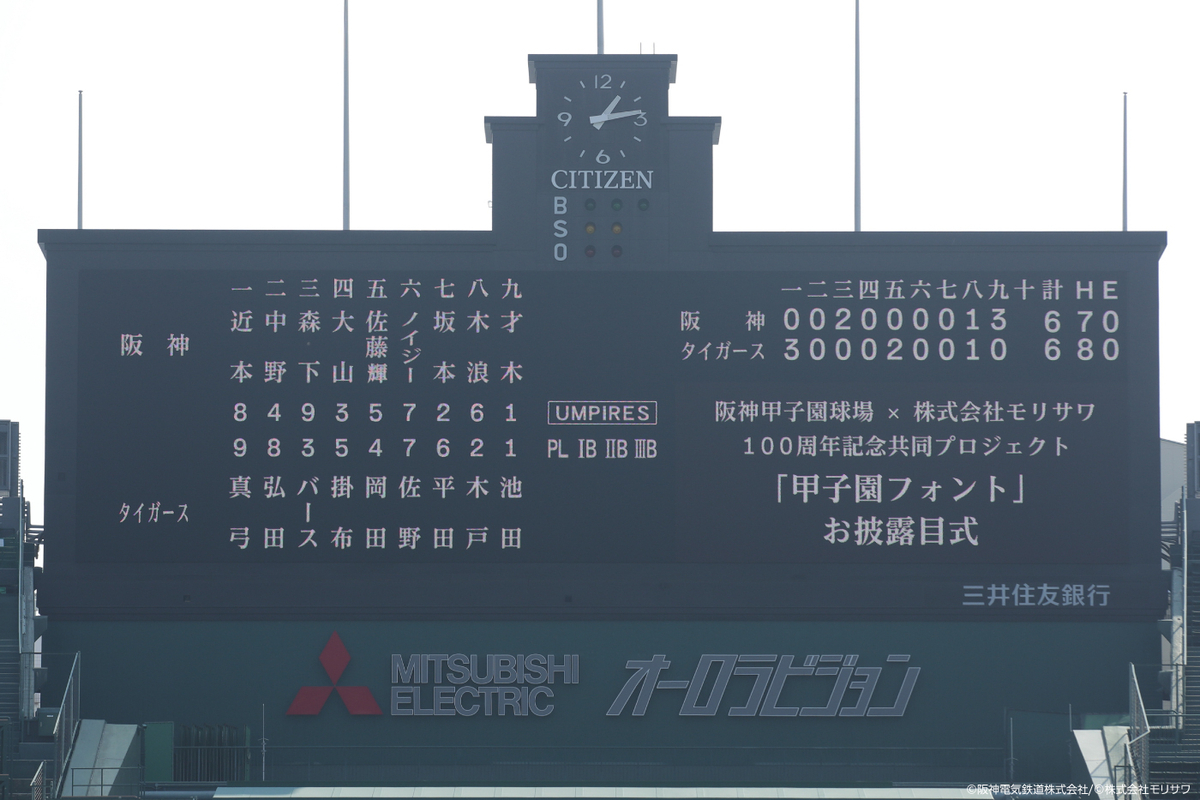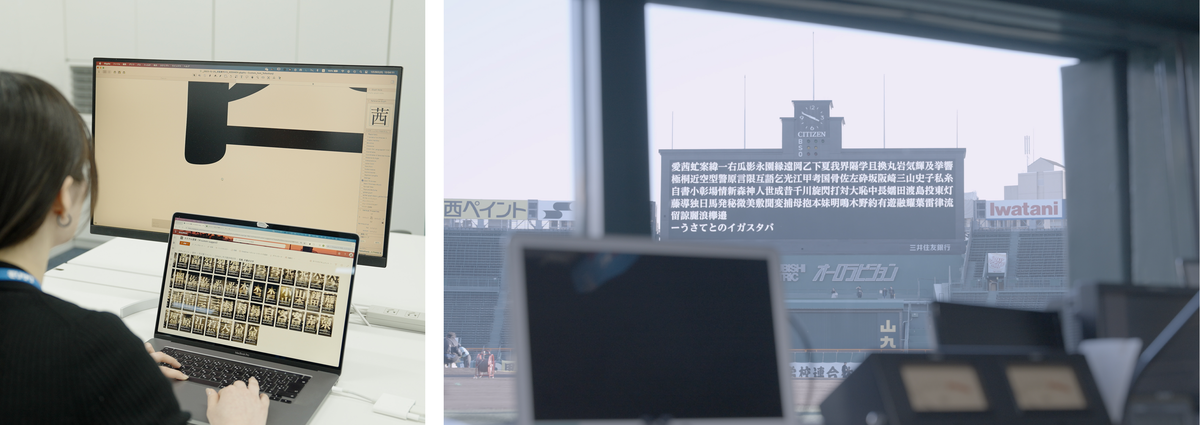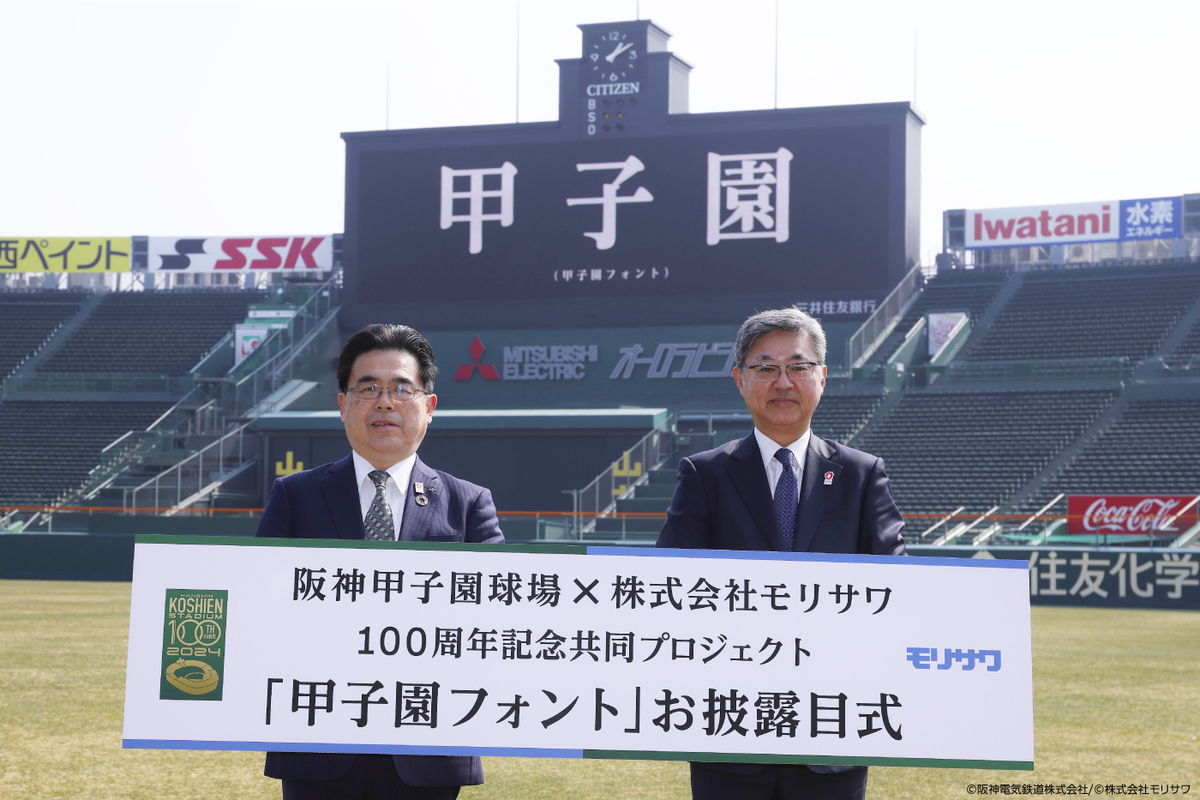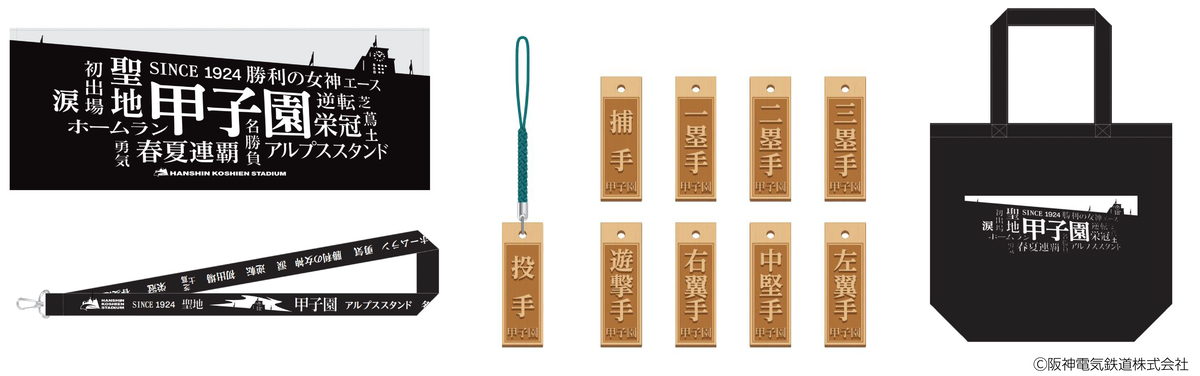
モリサワが阪神甲子園球場との100周年記念共同プロジェクト『甲子園フォント』お披露目式を開催 ~伝統と革新が融合した新たな『甲子園フォント』ついにお披露目~
モリサワは、阪神電気鉄道との100周年記念共同プロジェクト『甲子園フォント』を開発し、2025年2月27日に阪神甲子園球場でお披露目式を行った。
▼(上)選手名は阪神タイガースリーグ2023年優勝時のスターティングメンバー、(下)1985年開幕時のスターティングメンバー)
本プロジェクトは、阪神甲子園球場が大切に受け継いできた「甲子園文字」を、文字のプロフェッショナルとして歴史を紡いできたモリサワが、現代の実用に即した『甲子園フォント』として制作したもの。
『甲子園フォント』は、2025年シーズンから阪神甲子園球場のスコアボードで使用されるほか、タオルなどの球場オリジナルグッズにも使用される。
甲子園文字と『甲子園フォント』について
阪神甲子園球場のスコアボードでは、1983年まで、職人が黒い板に毛筆で手書きをした文字を使用しており、その独特な字形が「甲子園文字」として親しまれてきた。スコアボードを電光掲示に改修した1984年以降も、その伝統を受け継ぐべく、同球場の職員が甲子園文字を踏襲したオリジナルの文字を作り、表示することで、その伝統を受け継いできた。
『甲子園フォント』は、「甲子園文字」の伝統を次の時代に繋ぐコンセプトで、より多くの方の読みやすさに配慮したUD(ユニバーサルデザイン)フォントをベースとしている。甲子園文字の筆書きのニュアンスを取り入れながら、太みと文字サイズの調整を行って、ビジョンに表示された時も視認性を確保した明朝体として制作しました。また、スコアボード上で重要となる数字の書体は、甲子園文字ではゴシック体だったことから、今回も同様にゴシック体を継承している。
『甲子園フォント』の開発を記念して、開発の裏側を映したメイキング動画も公開。
動画では、当時の「甲子園文字」を知る元阪神タイガース・真弓明信氏にもインタビューして、手書きの甲子園文字の思い出や、新たな『甲子園フォント』について、「甲子園文字の力強さがありながらかっこいい」との感想も出ている。
▼手書きの甲子園文字の思い出を語る真弓明信氏(メイキング動画より)
▼甲子園フォントを開発中の様子
阪神甲子園球場におけるお披露目式
2025年2月27日に開催したお披露目式では、大勢の関係者や報道陣が集まり歴史的な瞬間を見届けた。
イベントでは事前レクチャーでプロジェクトメンバーが「甲子園文字」の歴史やフォント制作の背景について詳しい説明を行い、その後グラウンドに移動。甲子園球場の歴史や『甲子園フォント』制作の舞台裏を紹介する動画が流れた後、スコアボードに『甲子園フォント』が表示され、場内放送係員のコールに合わせて阪神タイガース2023年優勝時のスターティングメンバーと1985年の開幕時のスターティングメンバーの名が並んだ。
過去と現在の選手名が表示されるたびに、会場は大きな拍手と歓声に包まれた。
また、登壇者として阪神電気鉄道の谷本修取締役と、モリサワの森澤彰彦代表取締役社長が登場し、『甲子園フォント』の完成を祝った。
▼登壇者コメント
阪神甲子園球場では、スコアボードが手書きから電光式に変わってからも、甲子園文字を受け継ぐ、球場オリジナルの文字を作り、表示することでその伝統を継承してまいりました。
今回、モリサワ様の手により、甲子園文字のデザイン的特徴を受け継ぐ、『甲子園フォント』が開発され、デジタル表示における甲子園文字が完成形となったことで、これからの100年にも甲子園文字を受け継いでいけることを、大変嬉しく思っております。
この『甲子園フォント』が、多くのファンの皆様に親しまれ、これから生まれる名勝負、名選手たちとともに、新たな歴史を刻んでいってくれる事を願っています。
創業者が世界で初めて「邦文写真植字機」を発明してから100周年という記念すべきタイミングで、阪神甲子園球場様と共に「甲子園文字の伝統を次の時代に繋ぐ」というコンセプトの『甲子園フォント』開発プロジェクトに携わることができ光栄です。「文字を通じて社会に貢献する」を社是に、数々のフォントを作り続けているモリサワが、長年使用されてきた文字の特徴を活かしつつも、実用に即したユニバーサルデザインフォントをベースに、視認性を保つよう開発したフォントです。今後も長きにわたって『甲子園フォント』が野球ファンの皆様に愛されるものになりますよう願っております。
甲子園歴史館で開催中の「センバツ企画展2025」において、『甲子園フォント』に関する特別展示を開催。
甲子園文字の歴史や『甲子園フォント』プロジェクトの概要、フォント制作方法などをパネルで紹介する他、フォント制作の基となる原図や、原図の制作道具などの展示、2024年の阪神タイガース公式戦でモリサワが開催した、『甲子園フォント』制作を記念した冠試合の様子などを紹介している。